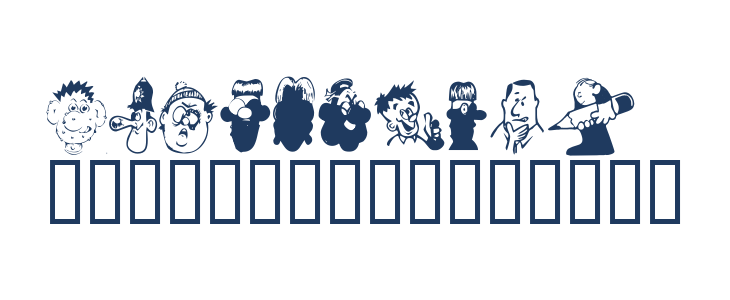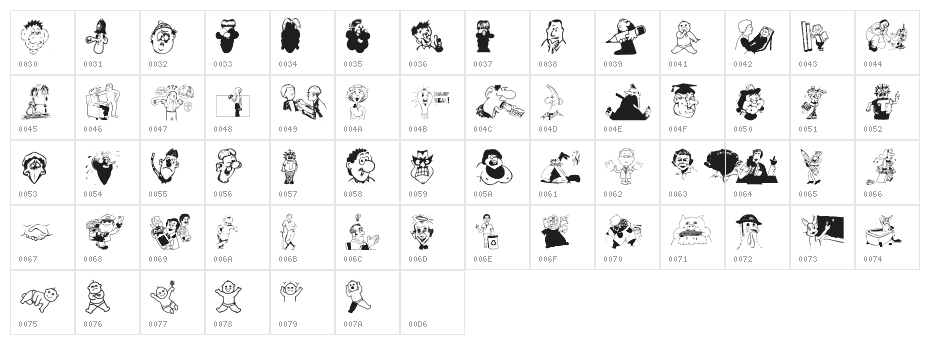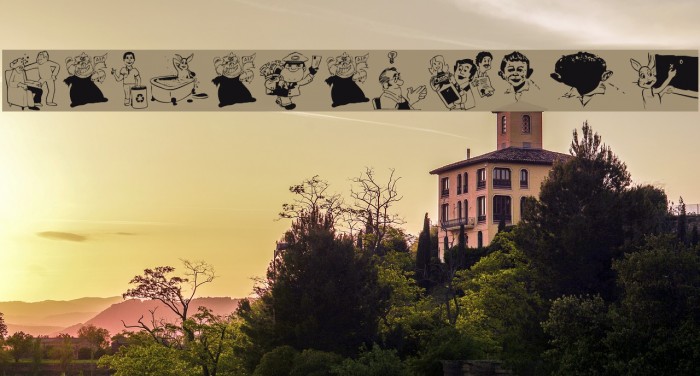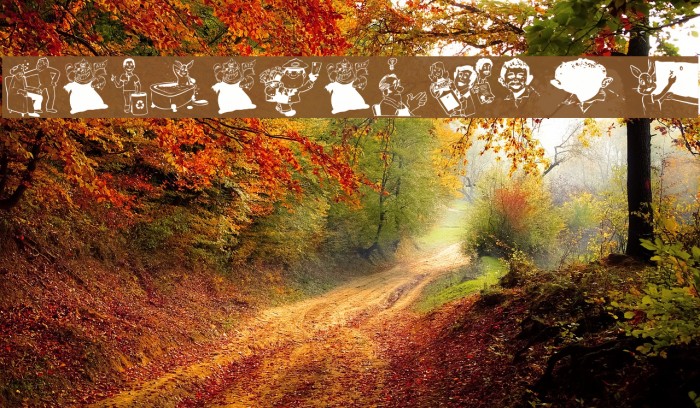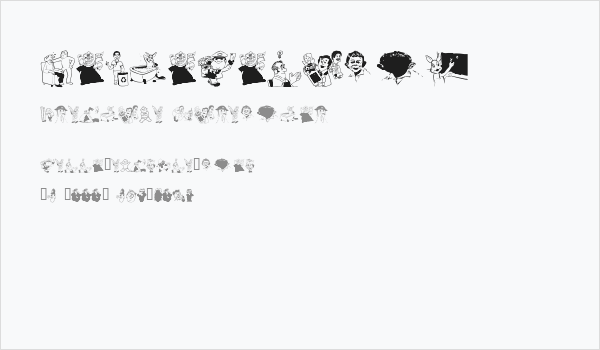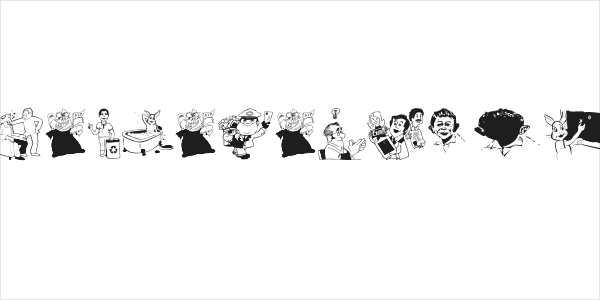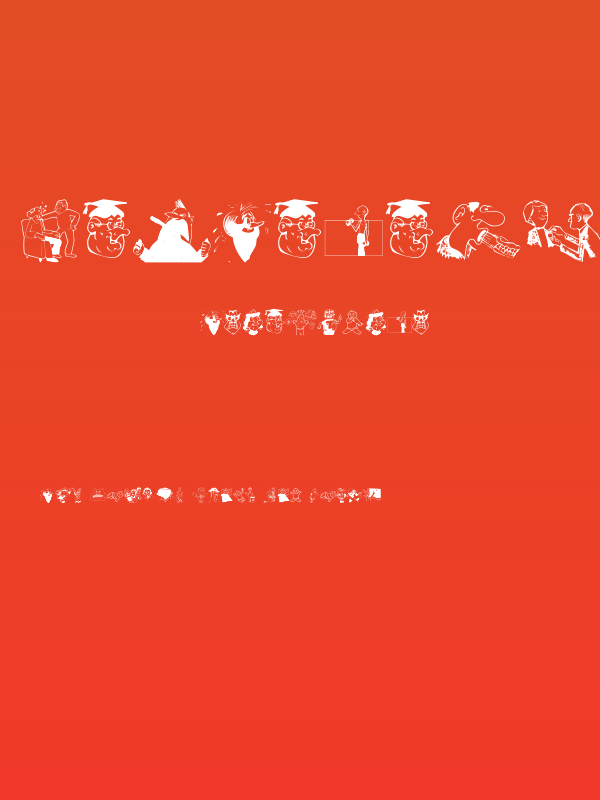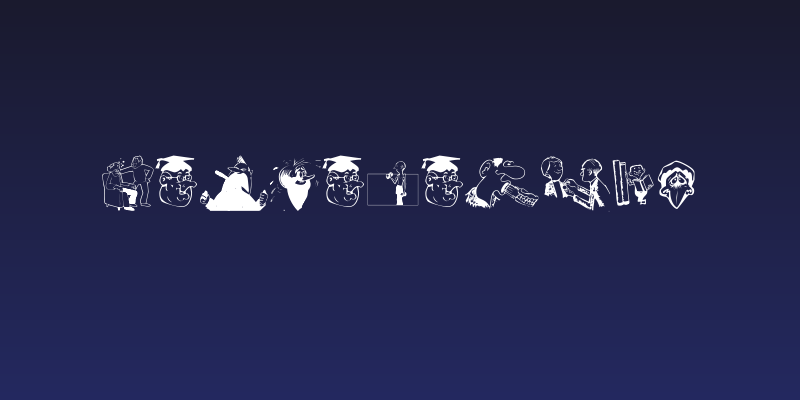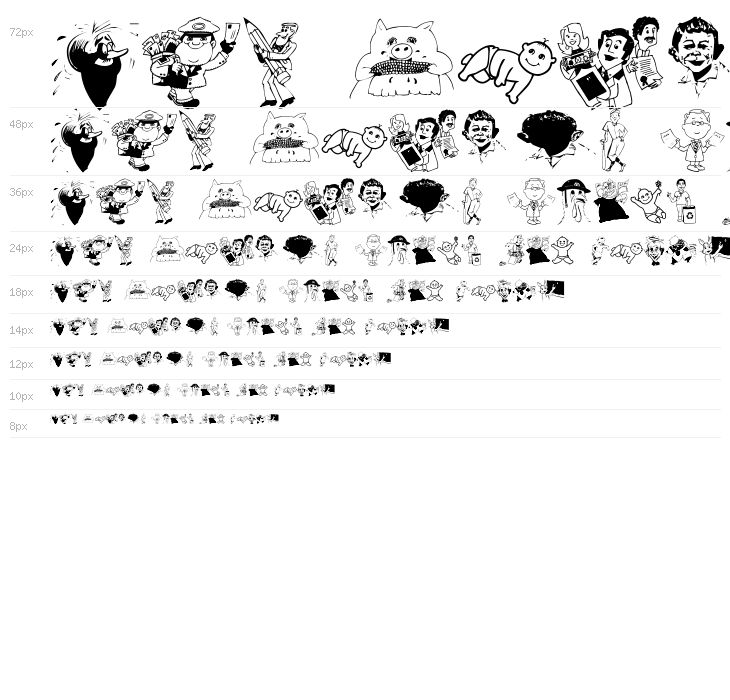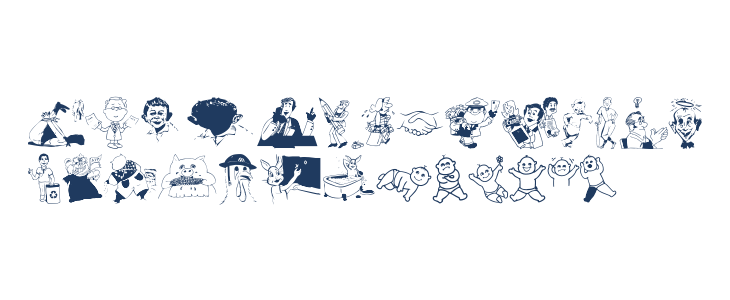
Fontoholics Font
✎ Cartoon
| Stile generale | Decorative, Playful, Cartoonish |
| Caso d'uso | Logos, Posters, Headlines, Themed graphics |
| Progetti proposti | Children’s books, comic strips, party invitations, playful branding, educational materials. |